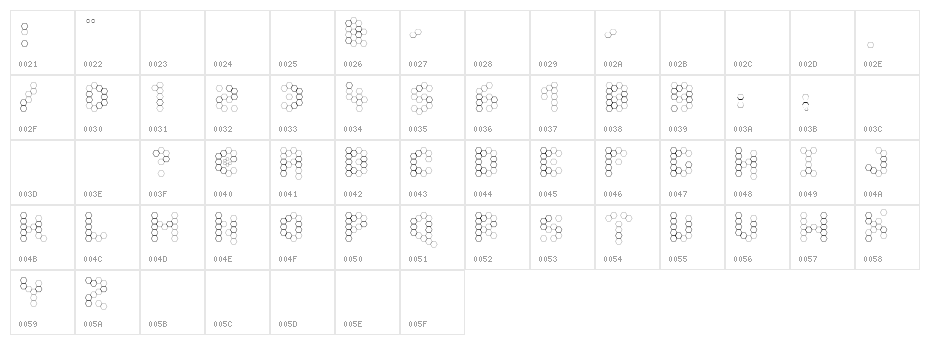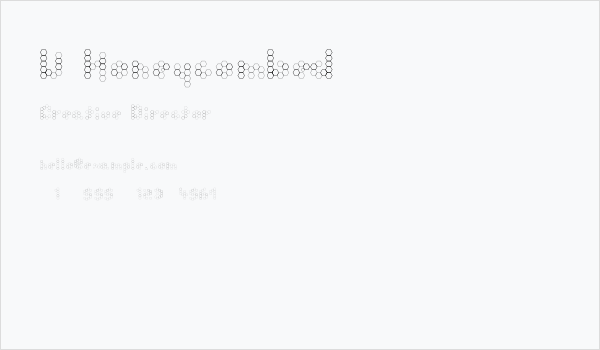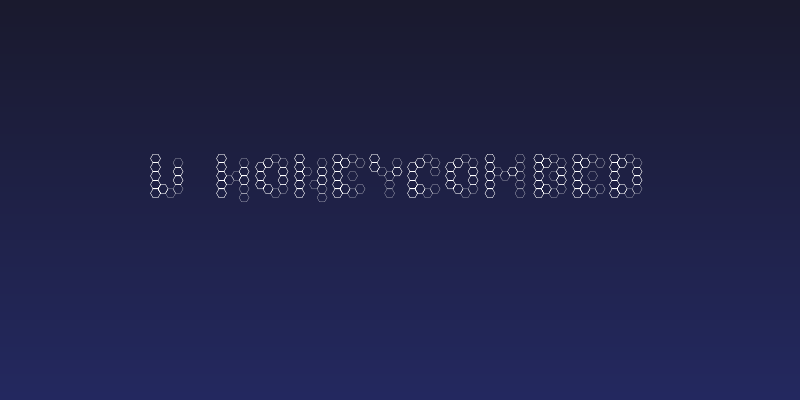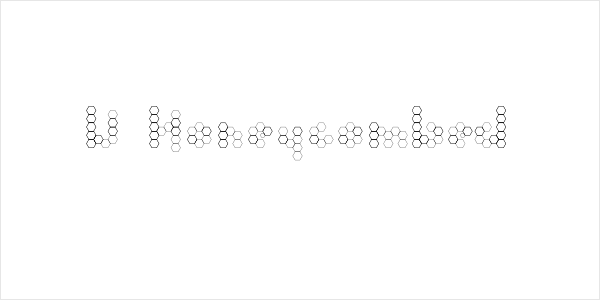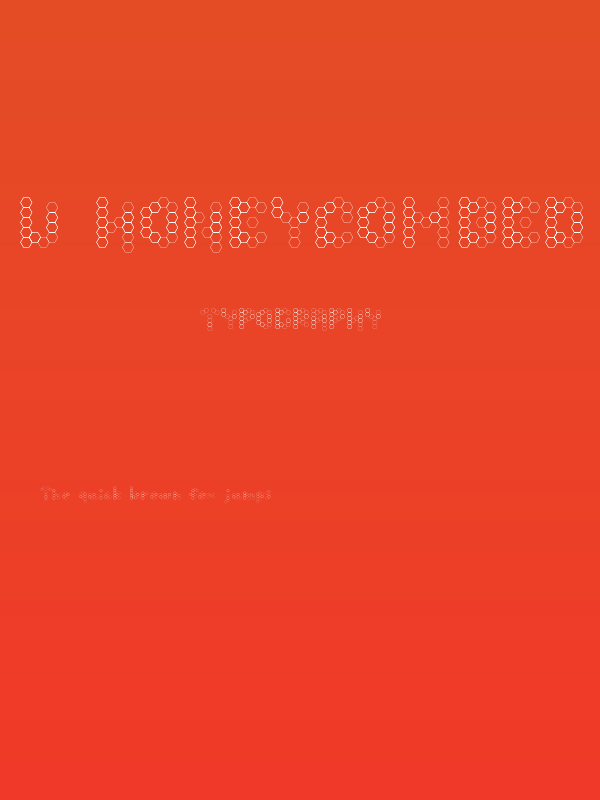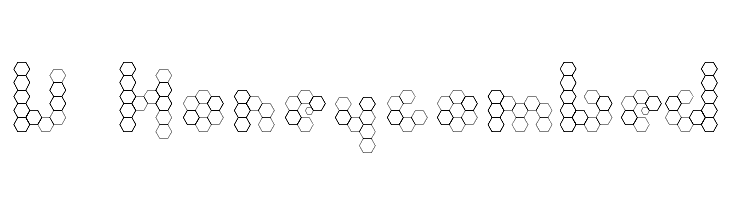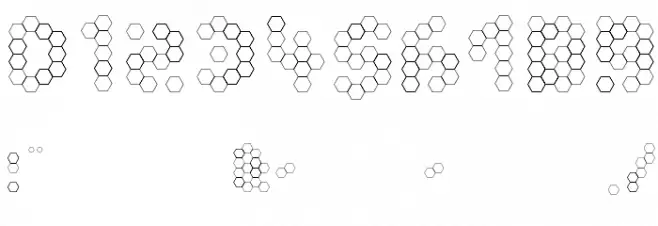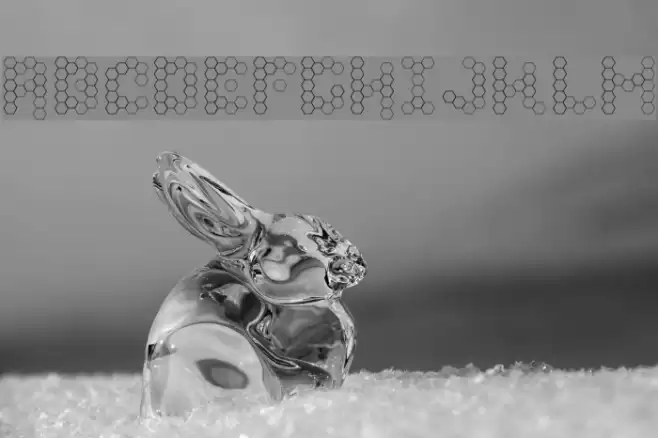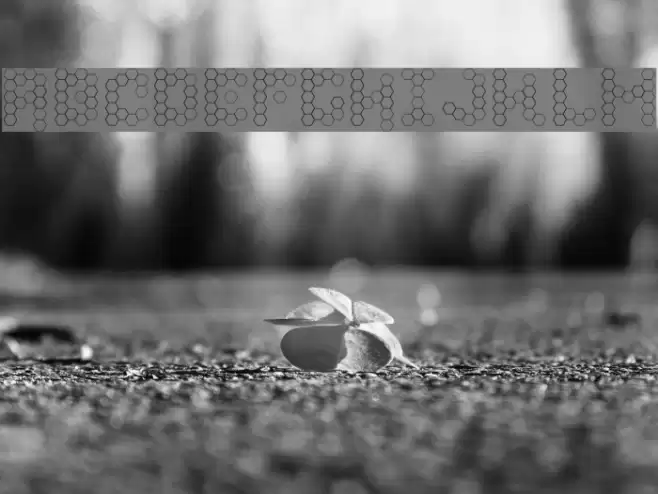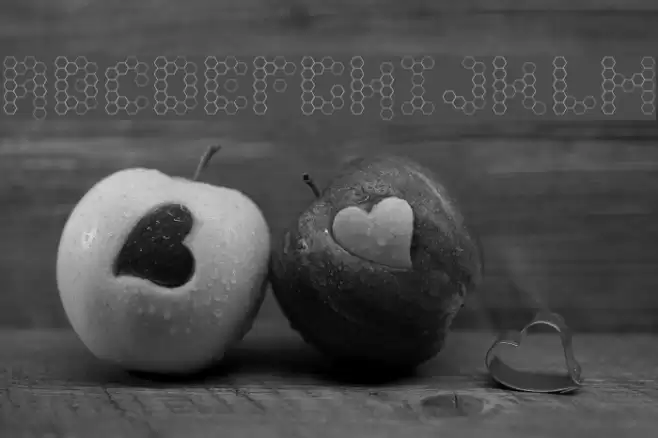
U Honeycombed Font
| Gesamtstil | Modern, Decorative |
| Anwendungsfall | Logos, Posters, Branding |
| Vorgeschlagene Projekte | Ideal for projects that require a modern and decorative touch, such as branding for eco-friendly products, nature-themed posters, or innovative tech company logos. |